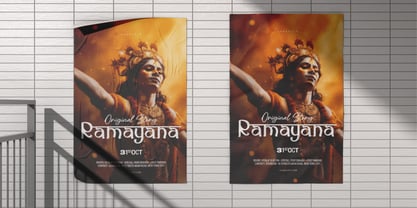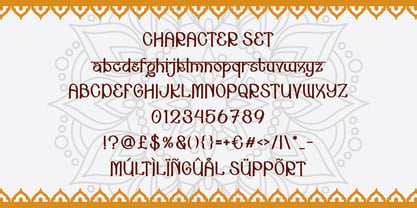
Maharaja
by Shanaf
The Maharaja Font Family was designed by Yesie Erma Yunita and published by Shanaf. Maharaja contains 1 styles. More about this family
Maharaja Hindi Display Font menghadirkan nuansa India yang kuat melalui bentuk huruf yang panjang, ramping, dan berirama lembut. Setiap karakter memiliki lengkungan khas yang menyerupai aksen kaligrafi Hindi, memberikan kesan tradisional namun tetap modern. Proporsi huruf yang tinggi menciptakan tampilan elegan, sementara ujung melengkung yang halus menambah sentuhan budaya yang hangat. Gaya ini memadukan elemen Sanskrit dan estetika Asia Selatan dengan struktur yang bersih sehingga mudah dibaca. Karakter yang sedikit ornamental membuat font ini terlihat artistik, namun tetap stabil untuk kebutuhan desain profesional. Maharaja Hindi Display Font cocok digunakan untuk proyek dengan tema India, budaya ASEAN, atau tampilan eksotis yang ingin menonjolkan identitas visual yang unik. Font ini ideal untuk logo, branding, poster, headline, kartu undangan, kemasan produk, buku, majalah, film title, stiker, dan proyek kreatif yang memerlukan kesan tradisional India yang kuat. Struktur garis yang tebal-tipis ringan menciptakan ritme visual yang menarik, sementara bentuk serif melengkung memberi rasa harmoni. Setiap huruf dirancang agar tampil tegas dalam ukuran besar, sehingga sangat efektif untuk iklan dan desain editorial. Font ini membantu desainer menyampaikan suasana cerita, tradisi, dan budaya India melalui tipografi yang autentik dan berseni. Maharaja Hindi Display Font memberikan pengalaman visual yang mampu memperkuat nilai estetika pada berbagai kebutuhan desain profesional.
Designers: Yesie Erma Yunita
Foundry: Shanaf